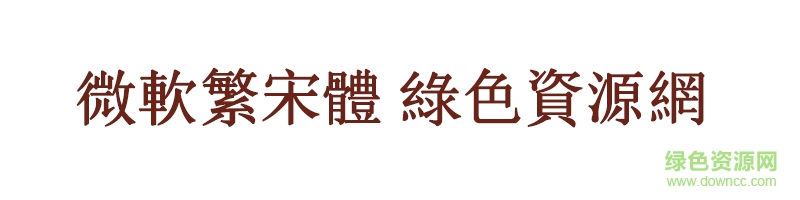
微軟繁宋體是一款基于中國(guó)書(shū)法字體宋體衍生而來(lái)的一款電腦字體,具備宋體橫輕豎重,橫線(xiàn)尾和直線(xiàn)頭呈三角狀,字形端正、剛勁有力的特點(diǎn),有喜歡的朋友可以來(lái)綠色資源網(wǎng)下載!
微軟繁宋體是一款應(yīng)用于平面設(shè)計(jì)方面的中文繁體字體,該字體端正大方,一筆一畫(huà)非常正氣,整體效果出眾,可適用于廣告設(shè)計(jì)、平面設(shè)計(jì)、印刷包裝等領(lǐng)域!